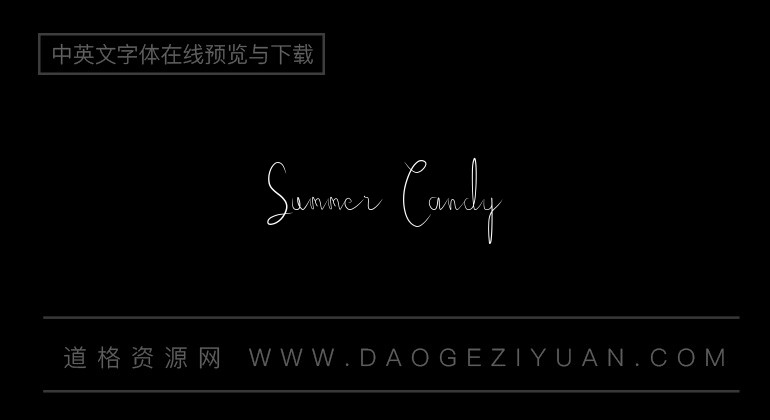
Summer Candy
Summer Candy 是一款可爱的涂鸦字体,由设计师Emily Spadoni设计。这款字体有趣可爱,充满夏日气息,有着清新的涂鸦风格,它的字母及数字都是用童趣的涂鸦风格绘制而成,充满了童真无邪的气息。Summer Candy字体可用于多种用途,如海报、招牌、T恤等,可以为设计作品增添活力和趣味。
Summer Candy是一款非常不错的手写艺术字体,具有很好的视觉感,适合于文化类的宣传设计、商业类品牌的广告和产品包装设计以及个性化文字排版等较多场景。